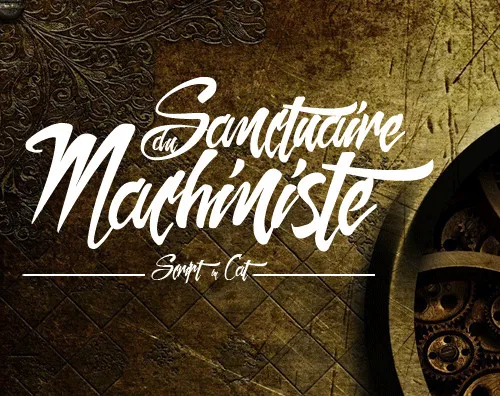
Sanctuaire Du Machiniste Font – Download Grátis
Escolhemos a fonte ‘Sanctuaire Du Machiniste Font’ para compartilhar por sua elegância handwritten única. Esta fonte foi criada pelo designer Hamilton, conhecida pela sua habilidade em criar personalidades únicas e sofisticadas. Ideal para aqueles que buscam um touch único nas suas criações digitais ou impressas. Ainda não tem a certeza se quer usar esta fonte? Basta contactar o designer diretamente para qualquer dúvida ou pedido de uso comercial. Hamilton é um criador respeitado e oferece suporte ao seu trabalho, garantindo que cada detalhe da sua arte seja preservado. Não hesite em entrar em contacto com ele através do email fornecido. A sua obra artística se tornará ainda mais atraente quando esta fonte é incorporada nas suas criações. Esta não apenas adiciona um toque especial à sua tipografia, mas também oferece uma maneira de manter o seu trabalho único e autêntico. Estamos certos de que esta font será uma escolha ótima para qualquer designer ou ilustrador que busque dar um toque personalizado a cada projeto.